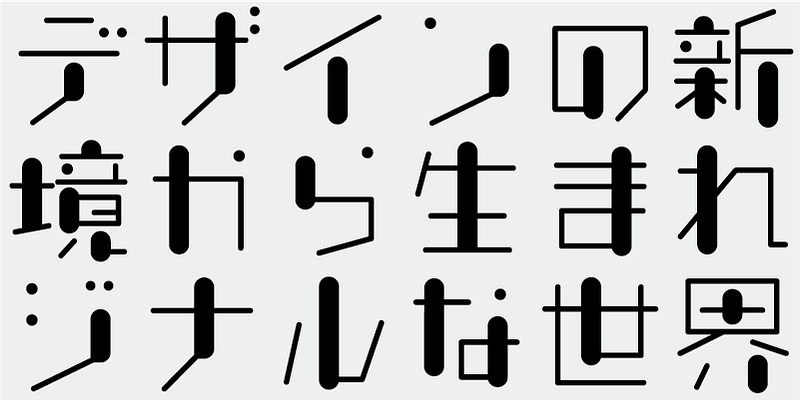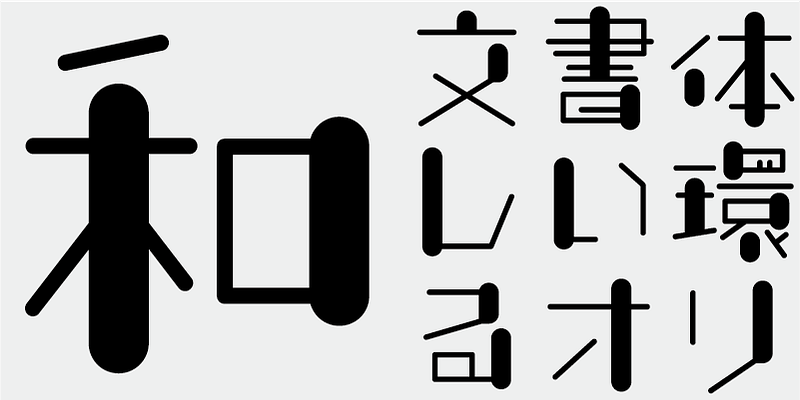
Esta fuente incluye 1000 caracteres kanji destacados elegidos de tablas de frecuencia de caracteres elaboradas por empresas de prensa, editoriales e institutos de estudios lingüísticos, además de 206 caracteres kana y signos de puntuación.
En la producción de fuentes japonesas de hoy en día, los 7000 caracteres del estándar JIS se consideran esenciales. Pero, ¿todas las fuentes realmente necesitan 7000 caracteres? En la época de la fotocomposición, se necesitaban muchos menos caracteres. FONT1000, un grupo de diseñadores de tipos de letra independientes, comenzó con esa sencilla pregunta. Hemos seleccionado el mínimo de 1000 caracteres kanji (ideográficos) necesarios para la composición tipográfica en japonés y nos hemos esforzado en crear tipos de letra y fuentes de forma activa para admitirlos. Este conjunto de 1000 caracteres kanji se seleccionó utilizando datos de frecuencia de caracteres recopilados por empresas de periódicos, editoriales, organizaciones de investigación lingüística, etc., y también incluye caracteres silábicos kana y signos de puntuación. FONT1000 se formó en 2001 con 25 diseñadores y 25 tipos de letra. Hoy tenemos 130 tipos de letra y hemos crecido hasta incluir casi 40 miembros, lo que hace posible trabajar con tipos de letra con más caracteres.